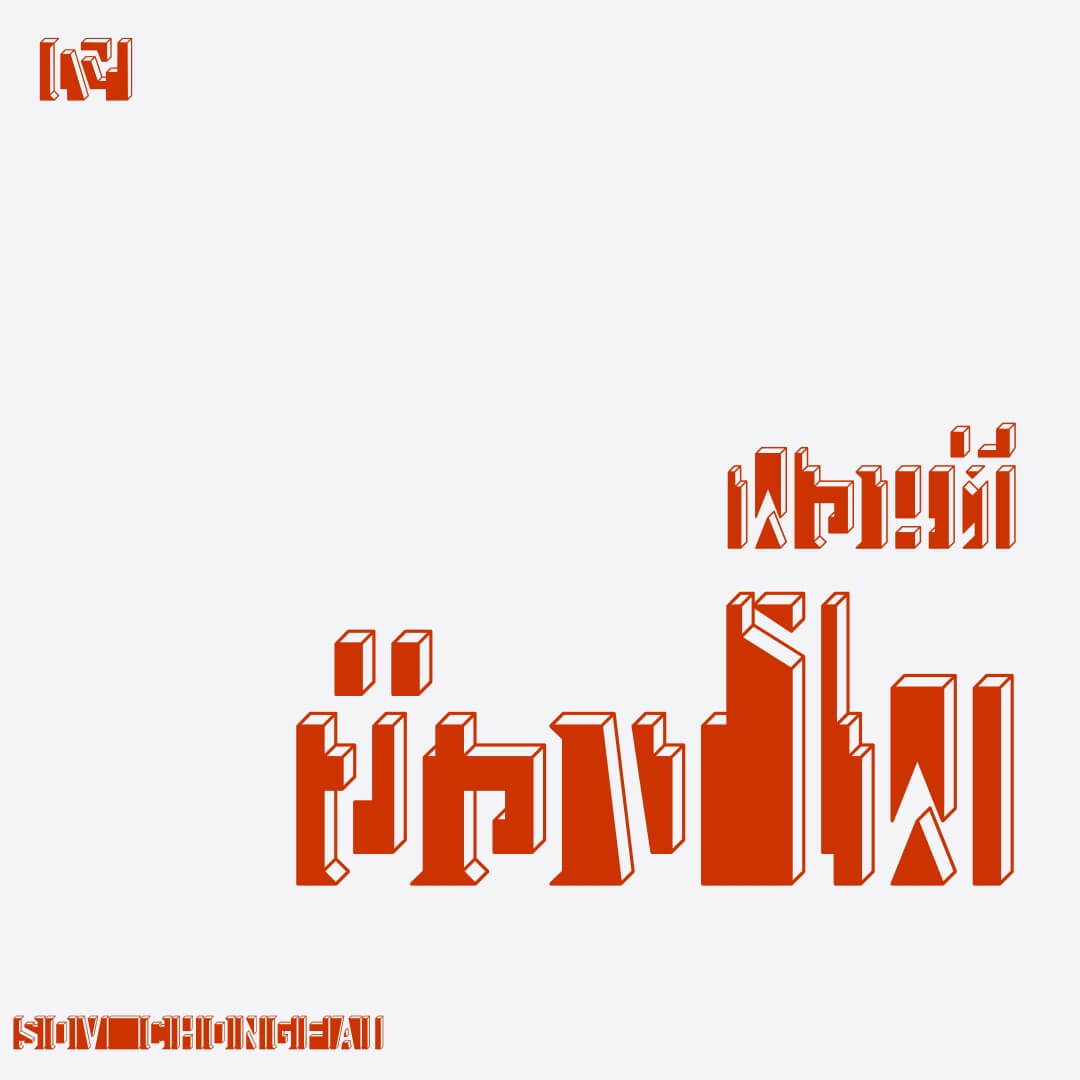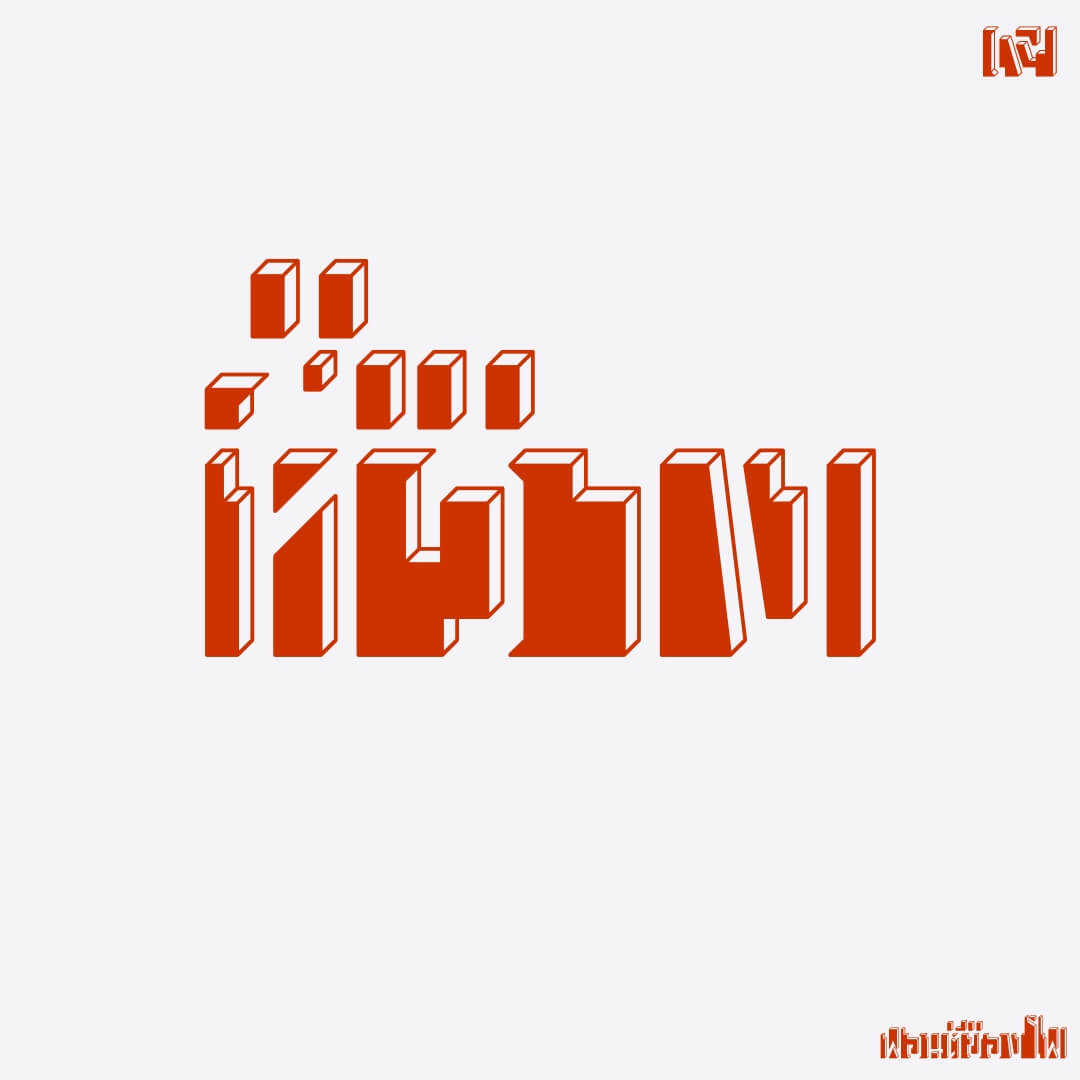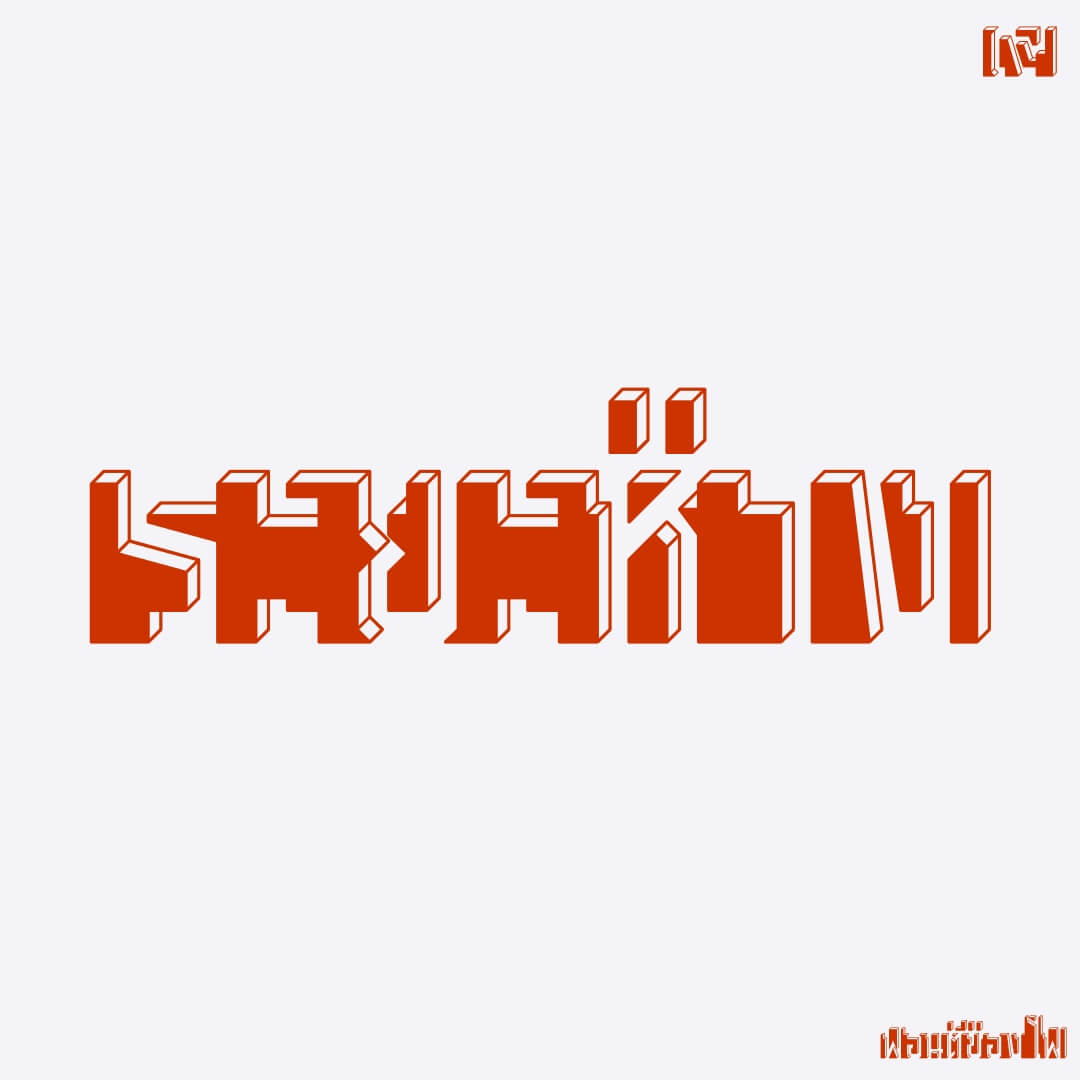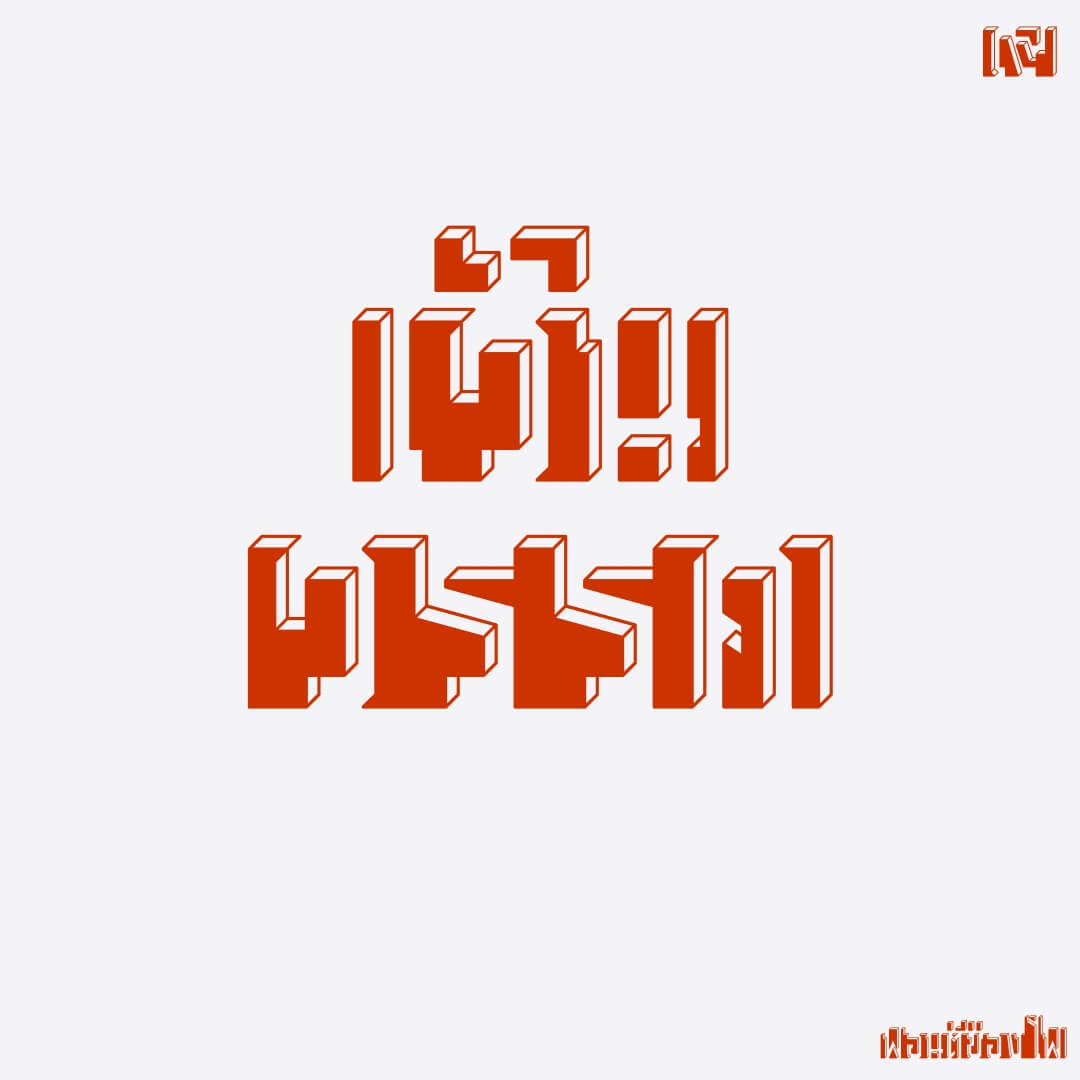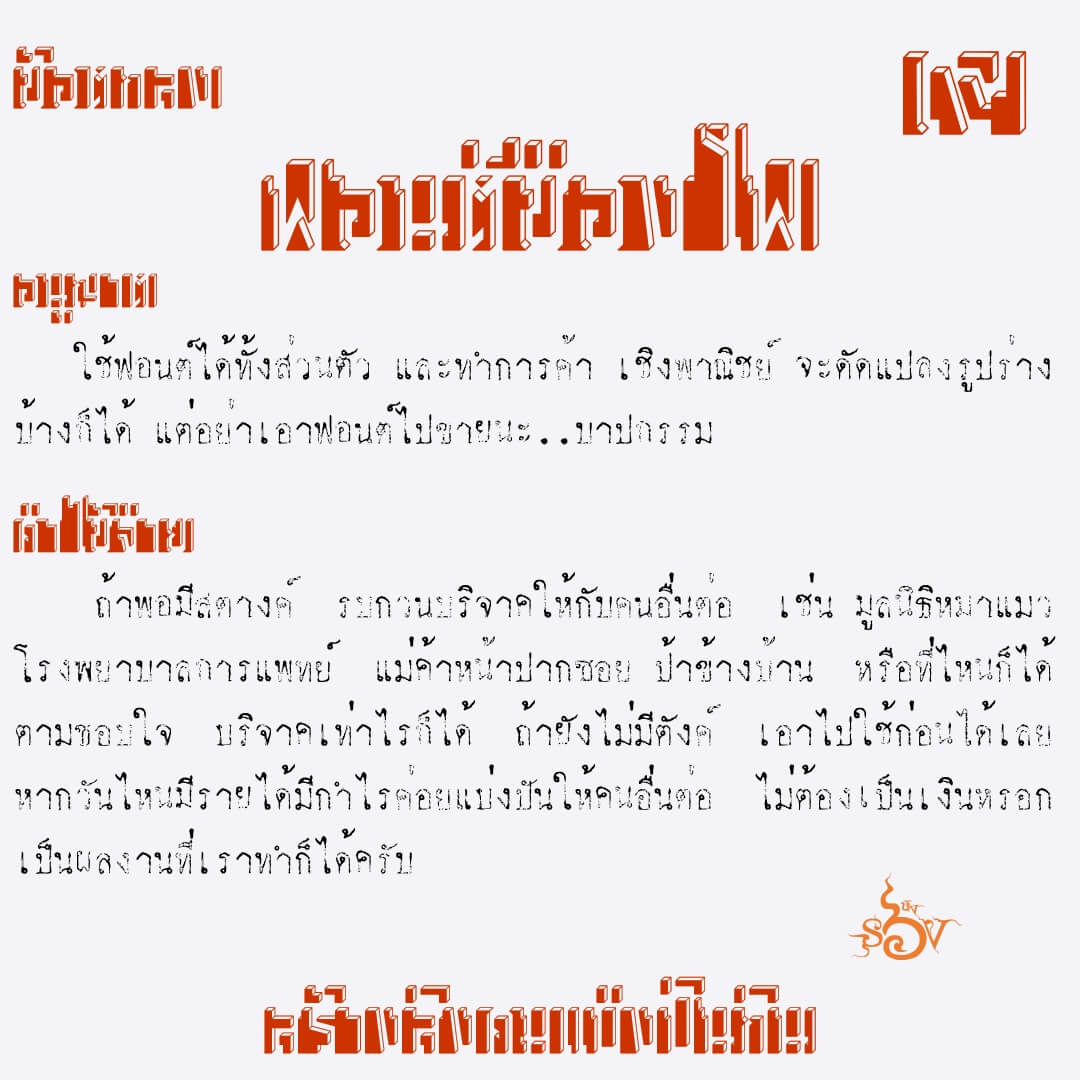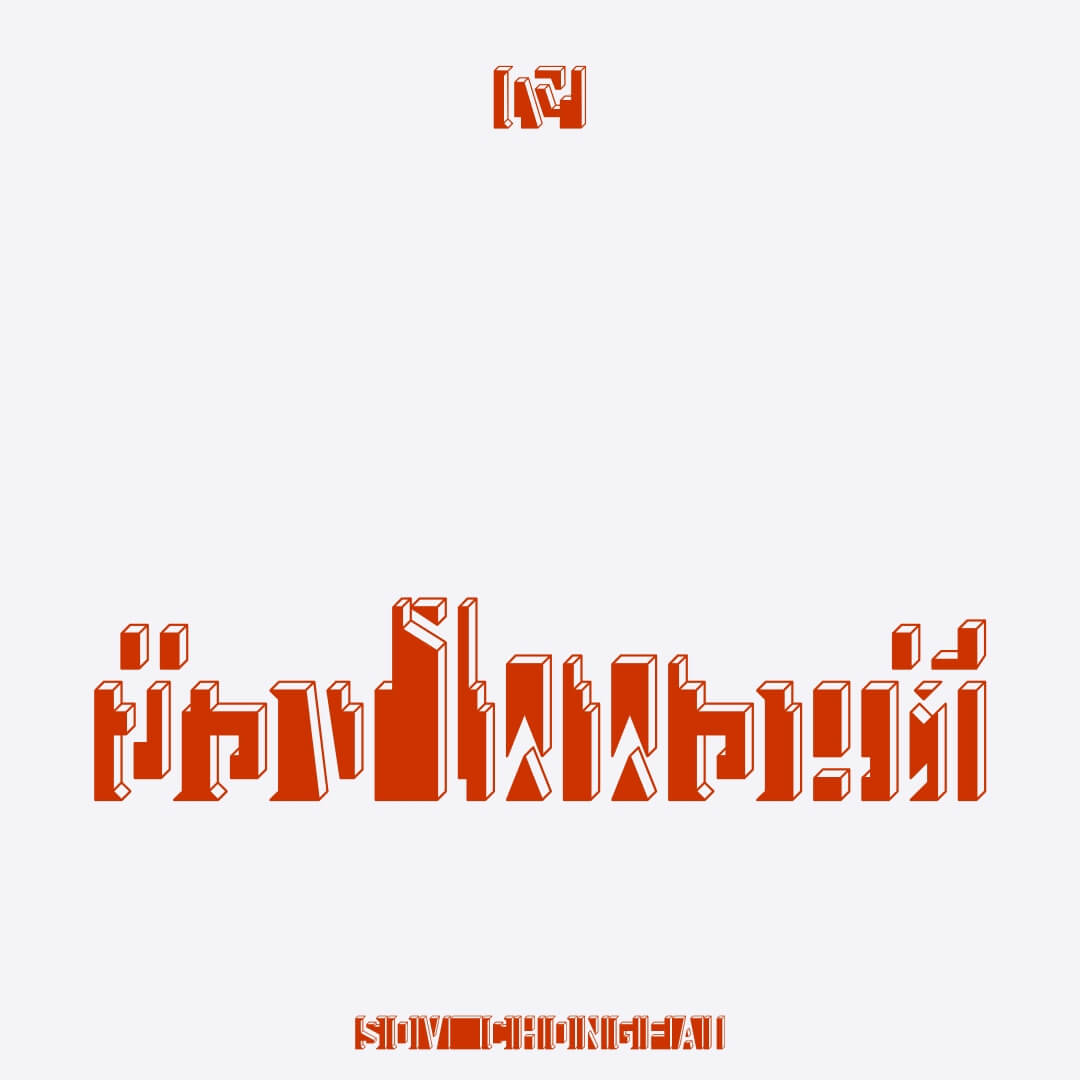
ฟอนต์ช่องไฟ – สำหรับฟอนต์… ช่องไฟสำคัญ แต่ไม่มีใครเห็น ก็เลยทำฟอนต์ให้ช่องไฟ… สรุปเห็นช่องไฟ แต่ไม่เห็นตัวอักษรแทน …ฮา
เบื้องหลังการออกแบบ : ฟอนต์ ช่องไฟ
ช่องไฟ (SOV_ChongFai)